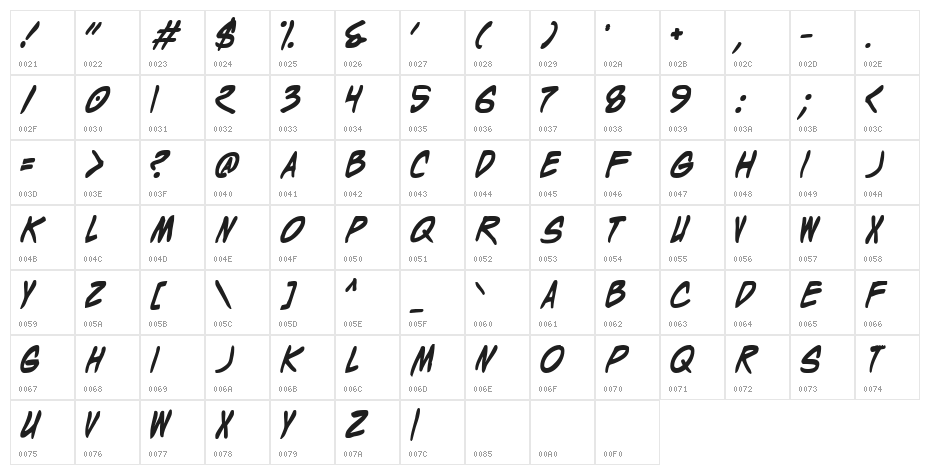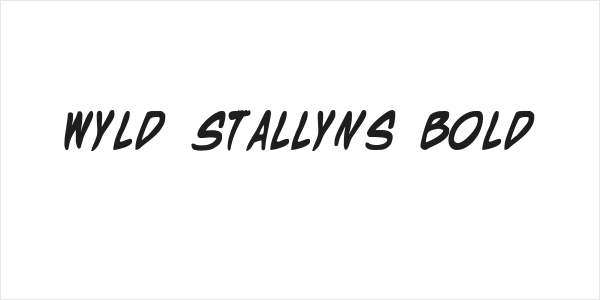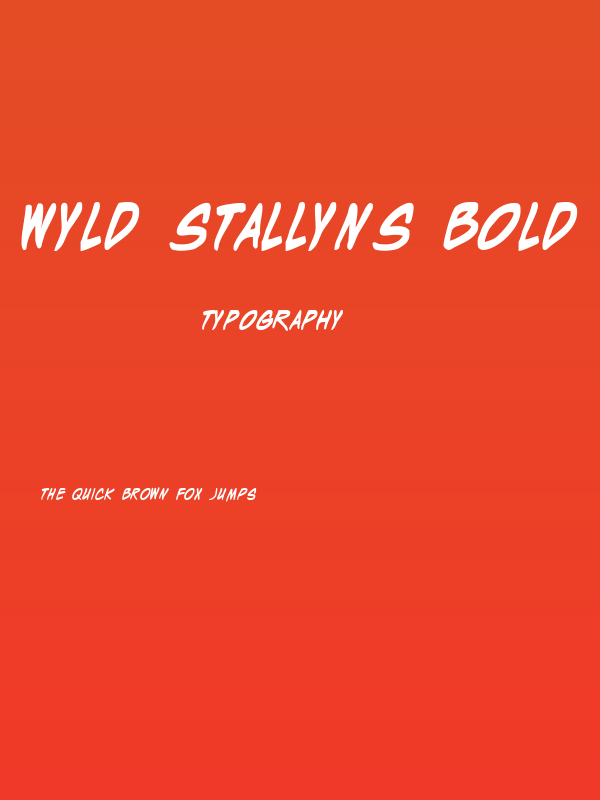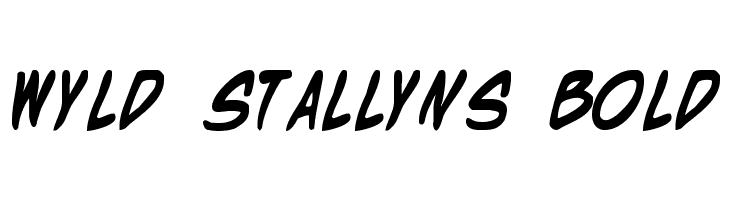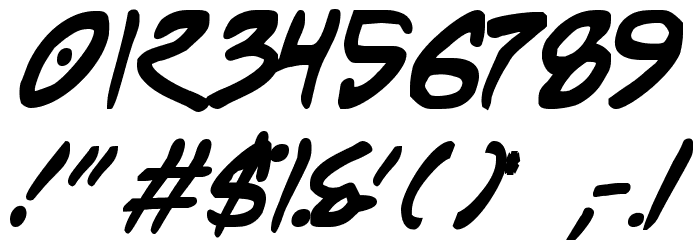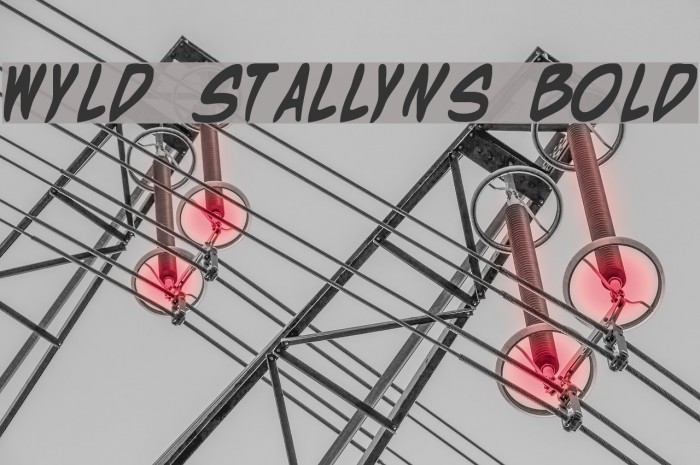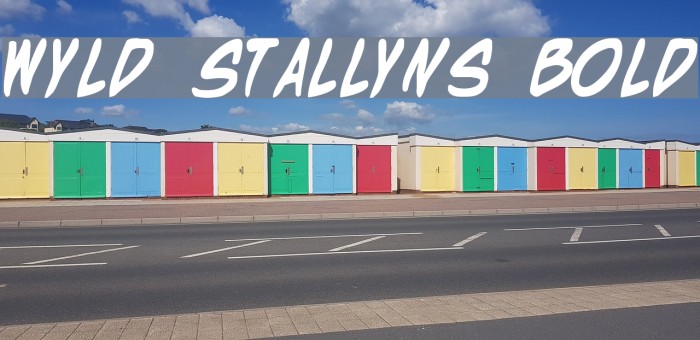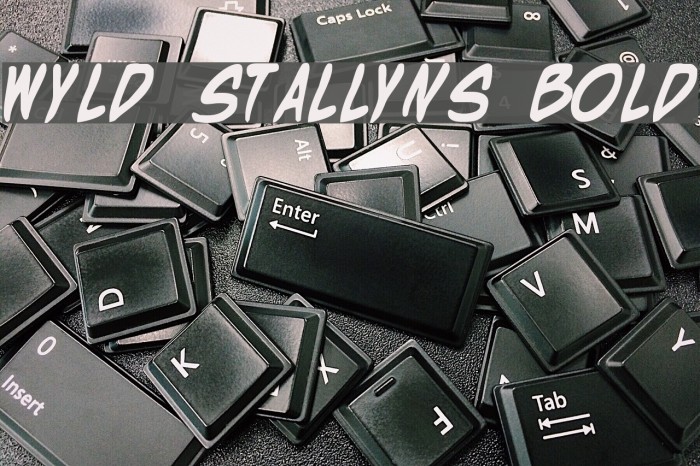
Wyld Stallyns Bold Font
| Vorgeschlagene Projekte | Ideal for posters, music album covers, event flyers, and branding that requires a lively and energetic feel. |